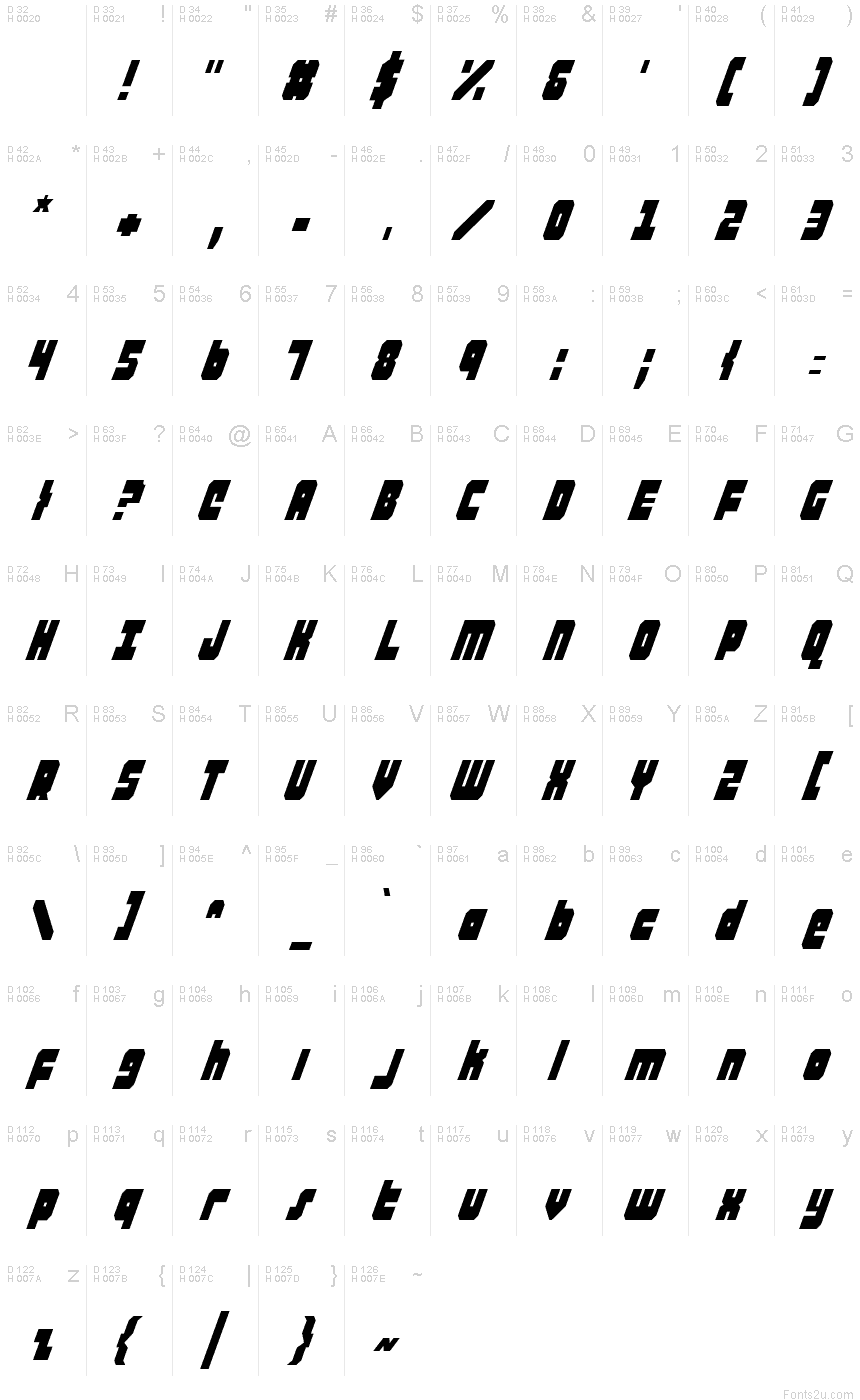
Alpha Taurus Condensed Italic od Iconian Fonts to darmowy, skondensowany, kursywny font typu techno display o futurystycznym, ostrym charakterze. Wielkie litery sprawiają wrażenie wyciętych z solidnych brył, a ciasny odstęp, kwadratowe narożniki i kanciaste diagonale nadają im szybki, pancerny wygląd, daleki od gładkiego, sci-fi połysku.
Krój ten naturalnie pasuje do logotypów gier, nagłówków plakatów, plansz tytułowych, okładek albumów i brandingu sportowego, gdzie krótkie słowa mogą wykorzystać ten skompresowany pęd do przodu. Jako darmowy font, świetnie sprawdza się również w przypadku odznak, monogramów i tekstów na okładkach, które wymagają surowego, mechanicznego uderzenia, zwłaszcza gdy zależy Ci na tym, by litery czytały się jako jeden, spójny blok ruchu.